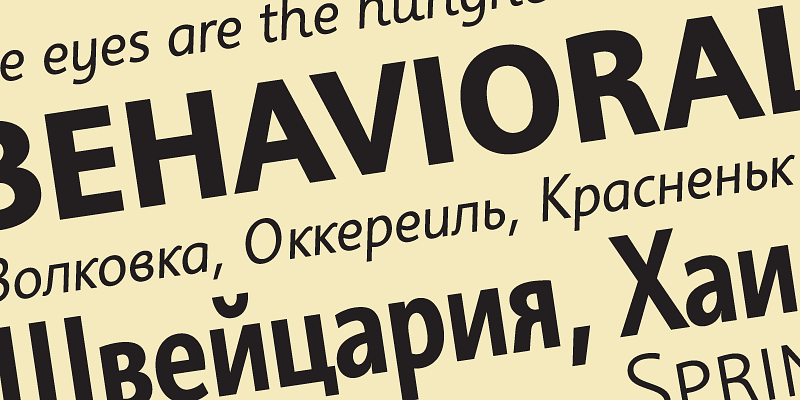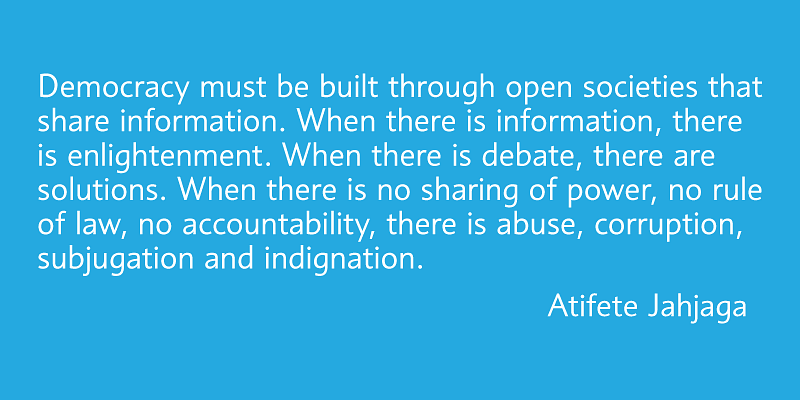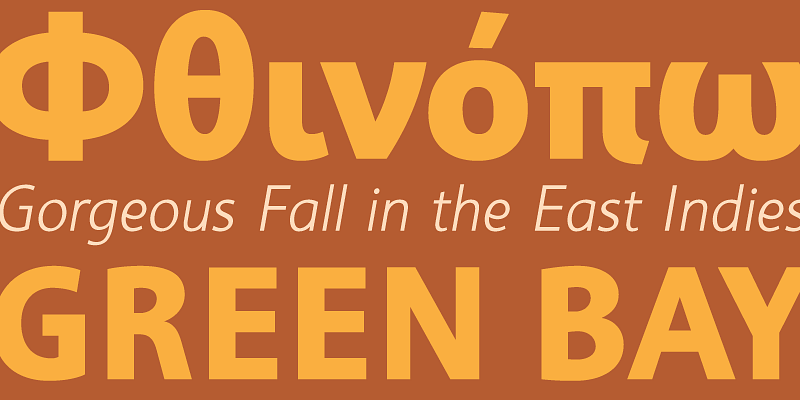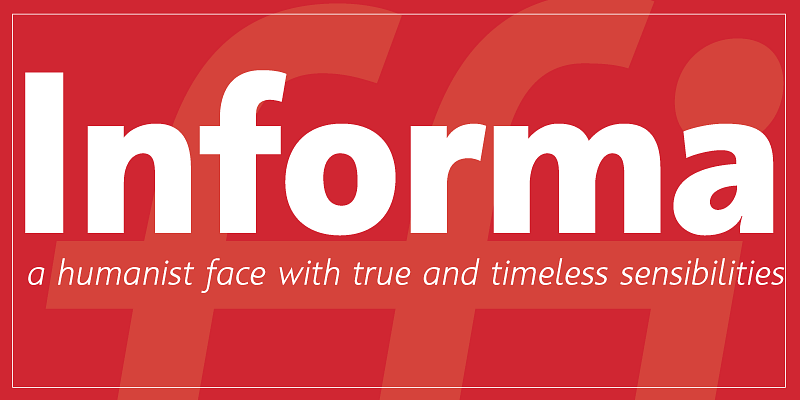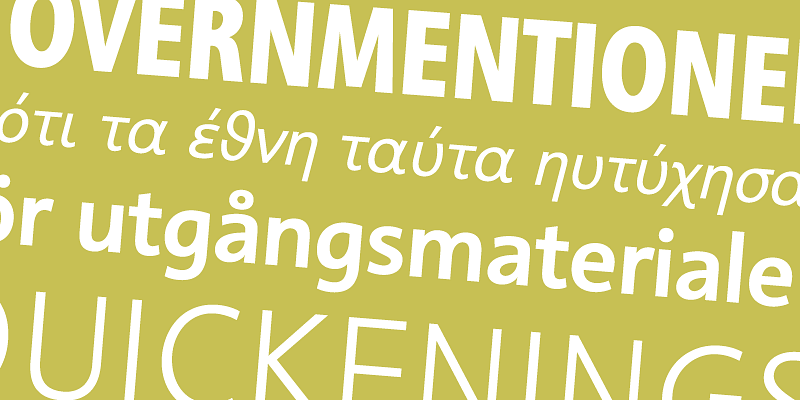
Informa ist eine umfassende serifenlose Schrift, die in Proportion, Rhythmus und Strichführung auf traditionellen Schriften basiert. Sie schafft ein visuelles Gleichgewicht zwischen Mensch und Maschine, indem sie das Gleichgewicht zwischen den Einflüssen, die das Genre bestimmen, aufrechterhält.